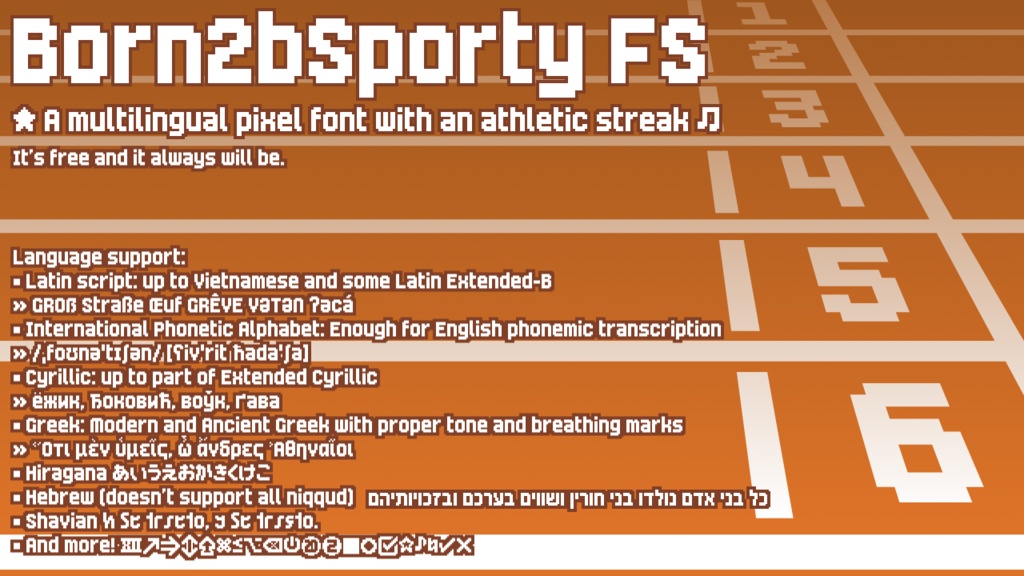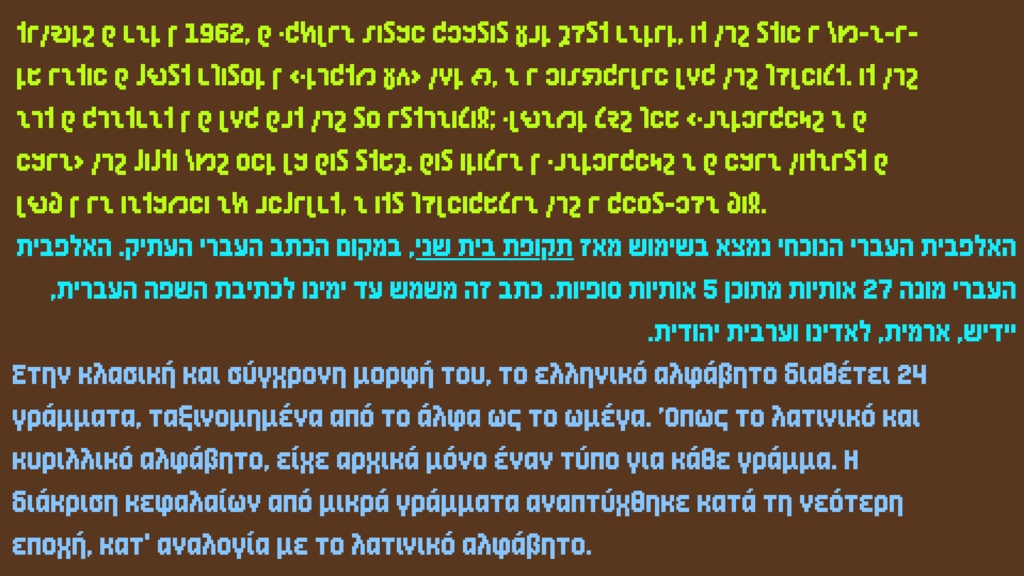
Born2bSporty FS ドット絵ひらがなフォント
昔作ったドットフォント「Born2bSporty」の改訂・拡張版です。かなり多言語対応なのが自慢です。 • ラテン文字: ラテン文字拡張Bの一部まで。ベトナム語対応。 • 国際発音記号(IPA): 主に英語の発音記号など、ある程度対応。 • キリル文字: キリル文字拡張Aの一部まで。メジャーなキリル文字表記の言語に対応(ウクライナ語、セルビア語など)。 • ギリシャ文字: 古代ギリシャ語のダイアクリティカルマークも対応。 • ヘブライ文字: 現代ヘブライ語に必要な部分は対応。 • ひらがな: 対応。 • ショー文字: 対応。 • 記号も多数対応。 原則、編集・派生も、商用利用も自由です。派生フォント作品を公開する場合、名前が被らないように変更してください。ソフトの組み込みも可能です。このフォントを使った画像出力を更に編集するのも可能です。できればフォントの出典をクレジットに記載していただければ幸いです。